8 ฟอนต์ไทย ฟรีใช้แล้วทำให้งานออกแบบดูดีทันตา
ฟอนต์ไทย ฟรีบอกเลยว่าการออกแบบไม่ว่าจะเป็นงานหนังสือ งานสื่อโฆษณา หรือปกรายงาน ส่วนสำคัญ 2 อย่างที่เป็นองค์ประกอบของงานต่าง ๆ คือ ภาพ หรืองานกราฟิก และอีกส่วนที่สำคัญและใช้สื่อสารต่อผู้พบเห็น คือ ตัวอักษร ตัวอักษรมีส่วนสำคัญในการสื่อสาร แต่ว่าถ้าเราทำงานออกแบบแต่ว่าใช้ฟอนต์ที่มีรูปแบบการออกแบบที่ไม่เหมาะสมกับงานเราก็จะรู้สึกว่าทำไมงานออกแบบของเราดูไม่ดี การเลือกใช้ฟอนต์เป็นอีก 1 ความลับของนักออกแบบที่จะต้องเรื่องใช้ฟอนต์ที่ดูดี และสื่ออารมณ์ได้ดีในงานของเรา ทั้งนี้ทางสำนักพิมพ์เราก็ใช้ฟอนต์ ในงานออกแบบมาอย่างหลากหลาย วันนี้จึงคิดว่าเราควรมาแนะนำฟอนต์ดีไซต์สวยงามใช้กับงานออกแบบไหนก็จะจำให้งานของเราดูดี เราจึงคัดสรรมาให้ดูกัน 8 ฟอนต์เลยทีเดียว ไปดูกันว่าเรามีฟอนต์อะไรมาแนะนำกันบ้าง
1. Promt
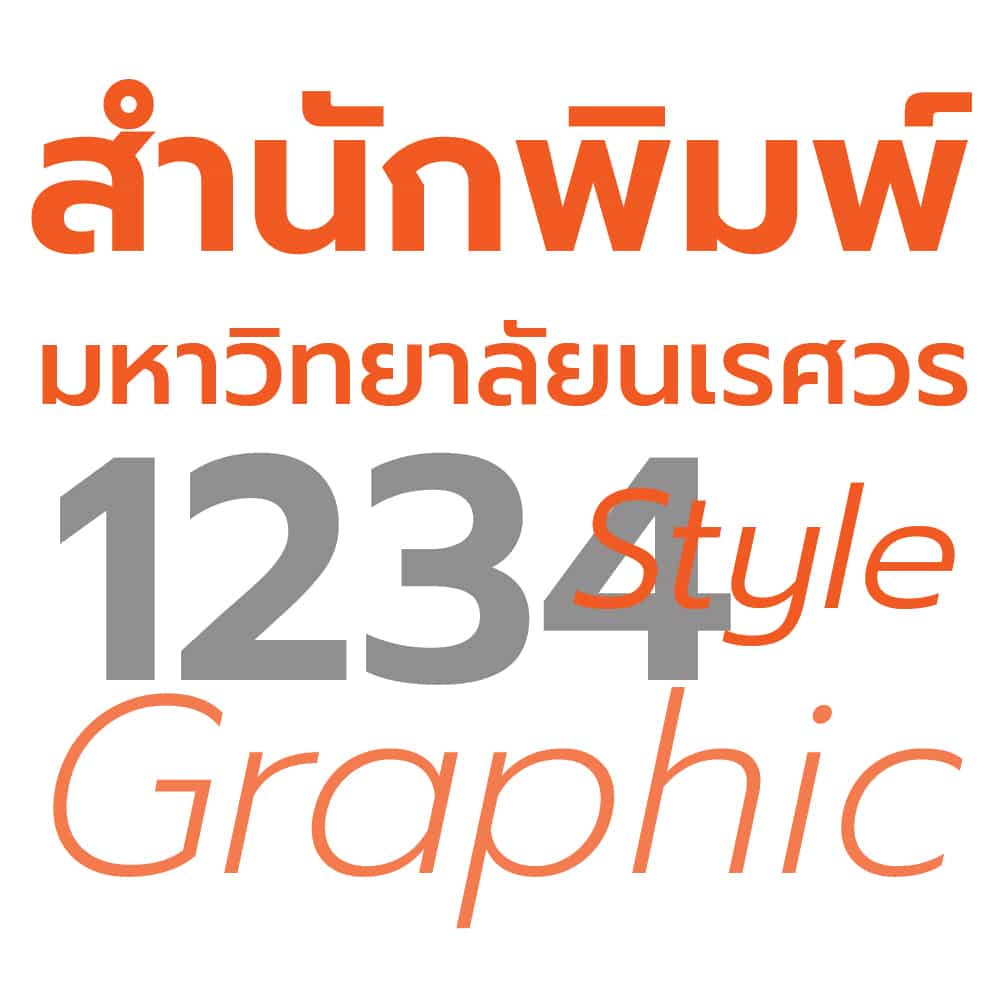
เป็น ฟอนต์ ไทย ที่ทาง Google ที่ออกแบบโดย Cadson Demak เป็นฟอนต์ลักษณะที่ไม่มีหัว เหมาะสำหรับการทำหัวเรื่อง หัวข้อ สื่องานโฆษณาต่าง ๆ ใครสนใจสามารถไปโหลดกันได้เลยที่นี่ Link
2. Kanit
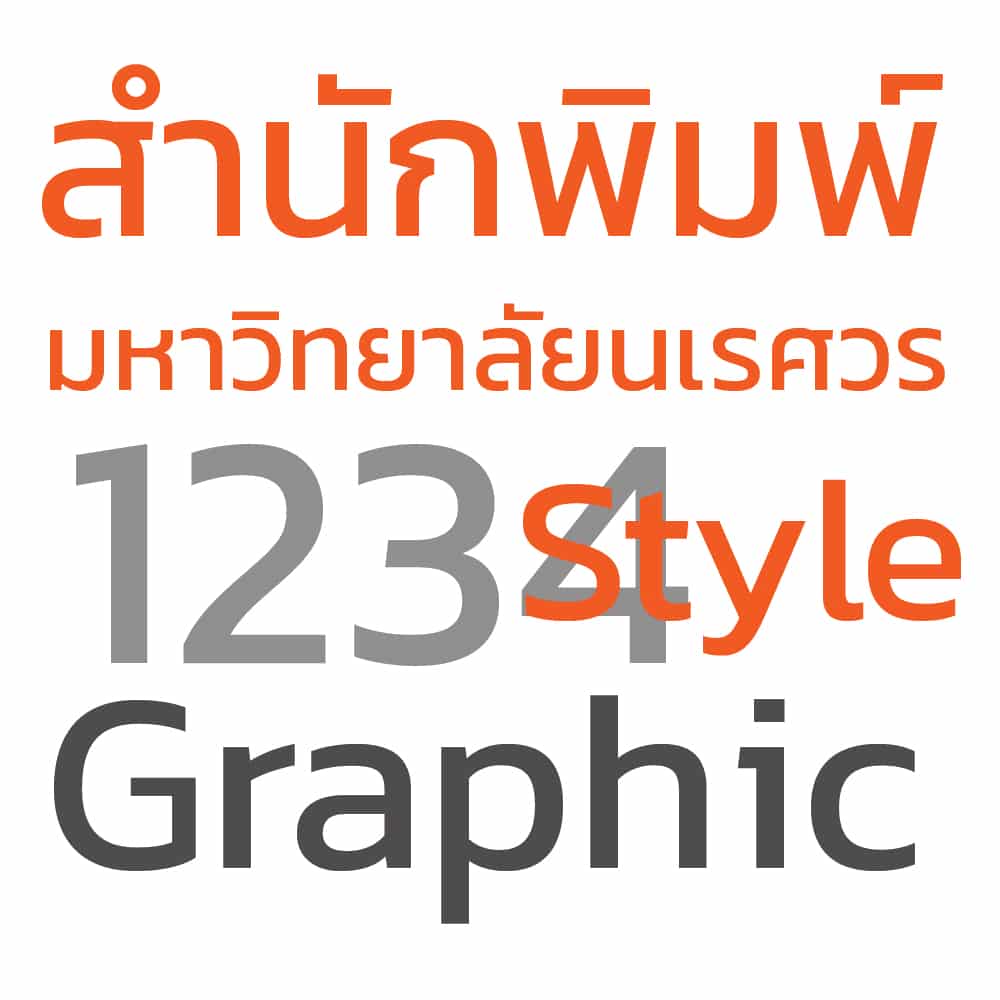
เป็นอีก 1 ฟอนต์ไทยที่ได้รับความนิยมอย่างมากจากทาง Google ที่ออกแบบโดย Cadson Demak เป็นฟอนต์ลักษณะที่ไม่มีหัวคล้าย ๆ กับฟอนต์ Promt เหมาะสำหรับ การทำปกหนังสือ ปกรายงาน หัวเรื่อง หัวข้อ สื่องานโฆษณาต่าง ๆ ใครสนใจสามารถไปโหลดกันได้เลยที่นี่ Link
3. Mitr
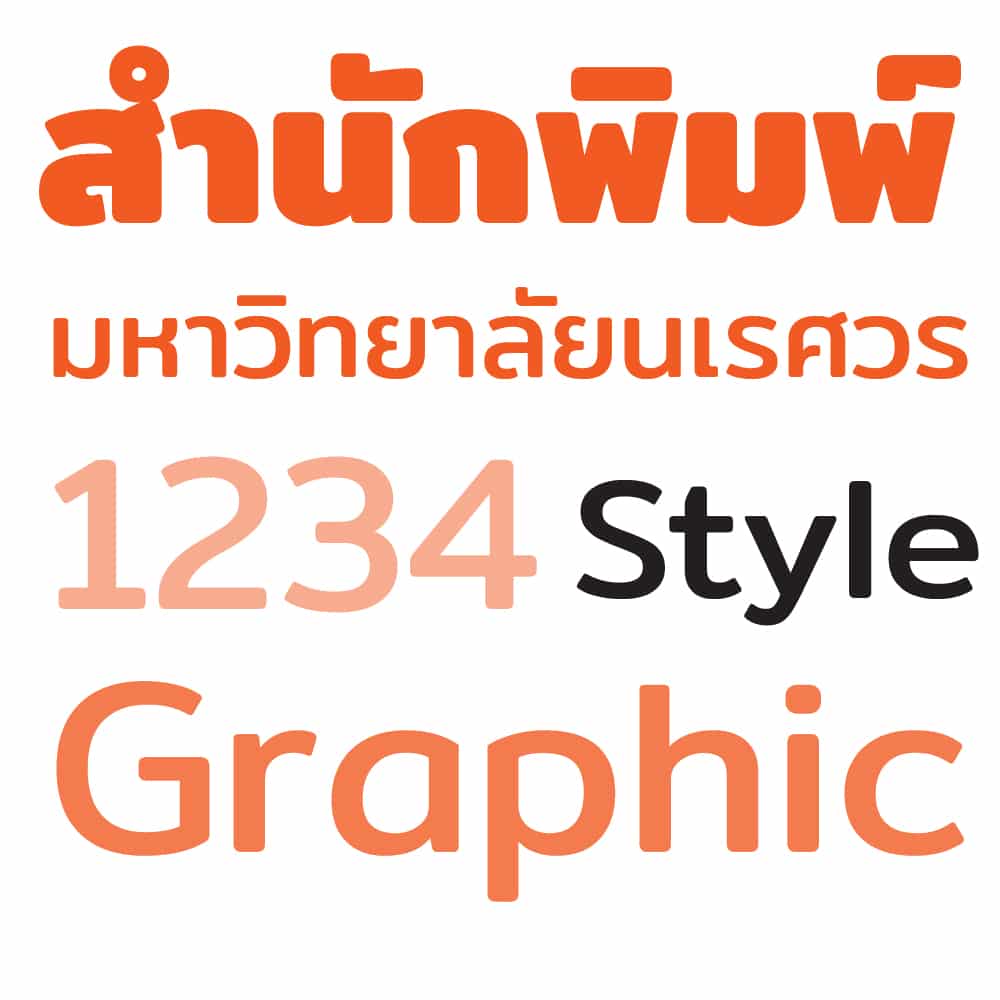
อีกฟอนต์ที่ได้รับความนิยมอย่างมากจากทาง Google เช่นเดิมที่ออกแบบโดย Cadson Demak เป็นฟอนต์ลักษณะที่ไม่มีหัวคล้าย ๆ แต่มีความละมุนออนโยน มีส่วนโค้งมากกว่าฟอนต์ Kanit หรือ Promt เหมาะสำหรับ การทำปกหนังสือ ปกรายงาน หัวเรื่อง หัวข้อ สื่องานโฆษณาต่าง ๆ ที่ดูไม่แข็งจนเกินไปทำให้งานออกแบบของเราดูสมูทมากยิ่งขึ้น ใครสนใจสามารถไปโหลดกันได้เลยที่นี่ Link
4. FC-lamoon
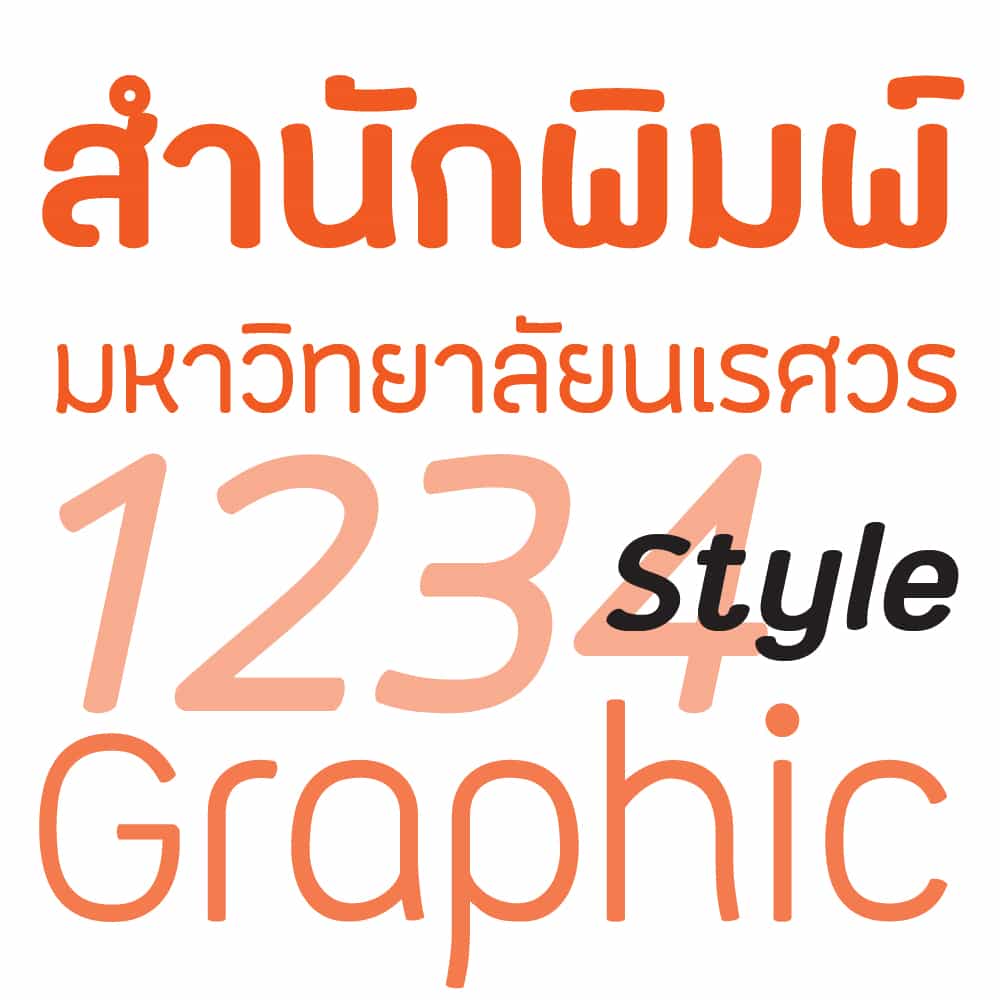
ฟอนต์ไทยที่ออกแบบมาด้วยความนุ่มนวล ลักษณะฟอนต์ที่ไม่มีหัว ให้ความรู้สึกที่สบาย ๆ เหมาะสำหรับ การทำปกหนังสือ ปกรายงาน หัวเรื่อง หัวข้อ สื่องานโฆษณาต่าง ๆ ที่ไม่ต้องการความตึงเครียดทำให้สื่อสารกับผู้พบเห็นได้สบาย ๆ มากยิ่งขึ้น สนใจสามารถไปโหลดกันได้เลยที่นี่ Link
5. Cloud
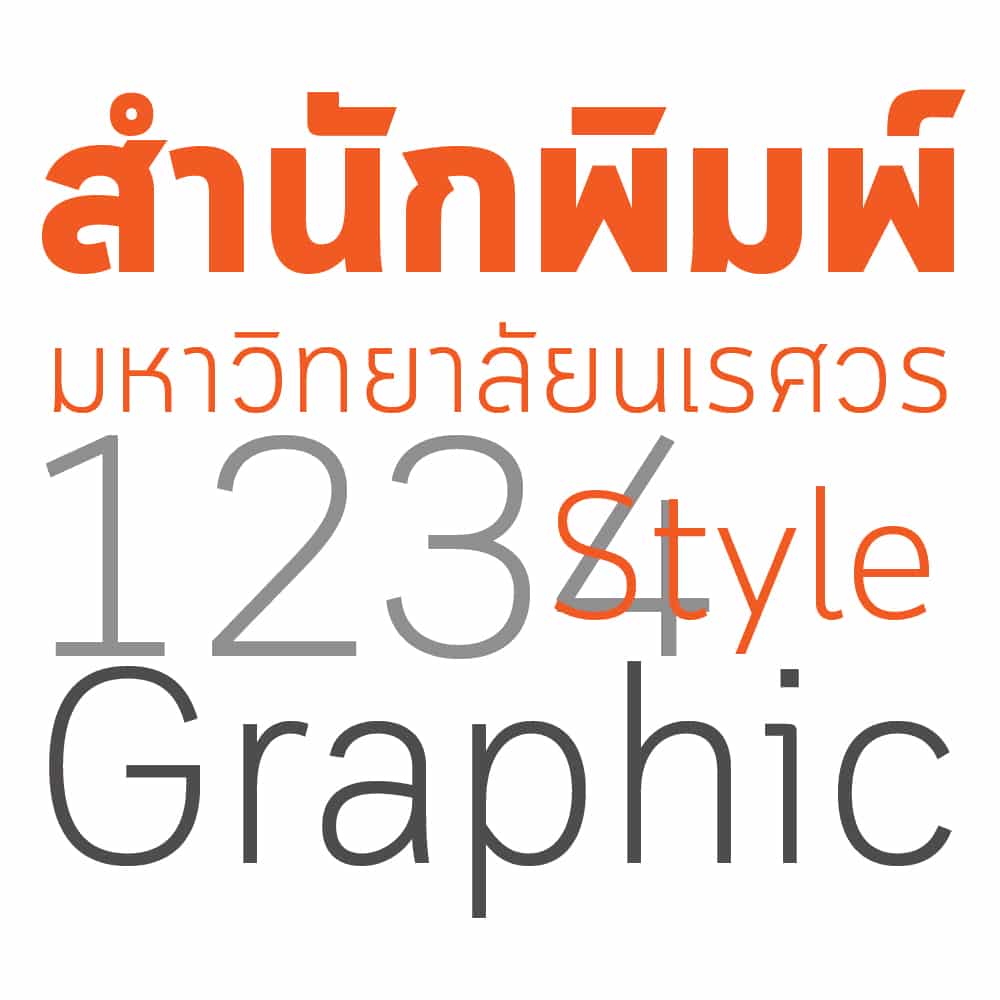
เป็นอีกฟอนต์ที่ทีมงานออกแบบชอบใช้ เหมาะสำหรับ การทำปกหนังสือ ปกรายงาน หัวเรื่อง หัวข้อ สื่องานโฆษณาต่าง ๆ ทำให้งานขอเราดูเป็นทางการและมีความน่าเชื่อถือมากยิ่งขึ้น ให้อารมณ์ที่แข็งแกร่ง ใครสนใจสามารถไปโหลดกันได้เลยที่นี่ Link
6. Supermarket
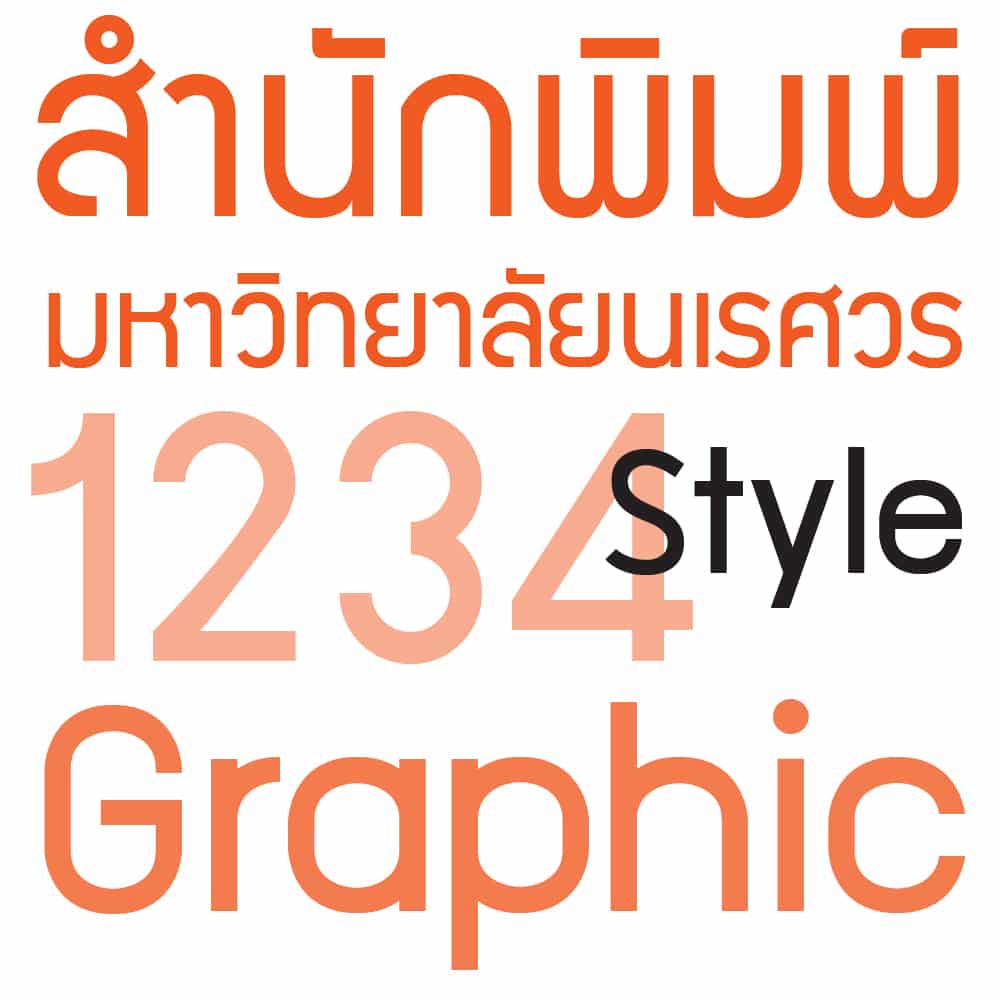
ฟอนต์ในตำนานที่เมื่อนักออกแบบพูดถึงฟอนต์ที่เป็นลักษณะไม่มีหัวและใช้งานใบการออกแบบแรก ก็คงต้องตอบเป็นเสียงเดียวกันว่า Supermarket ซึ่งปัจจุบันก็ยังเป็นดาวค้างฟ้าที่ยังคงได้รับความนิยมเป็นอย่างมาก เหมาะสำหรับ การทำปกหนังสือ ปกรายงาน หัวเรื่อง หัวข้อ สื่องานโฆษณาต่าง ๆ ทำให้งานขอเราดูเป็นทางการและมีความน่าเชื่อถือ ใครสนใจสามารถไปโหลดกันได้เลยที่นี่ Link
7. Sukhumvit Set
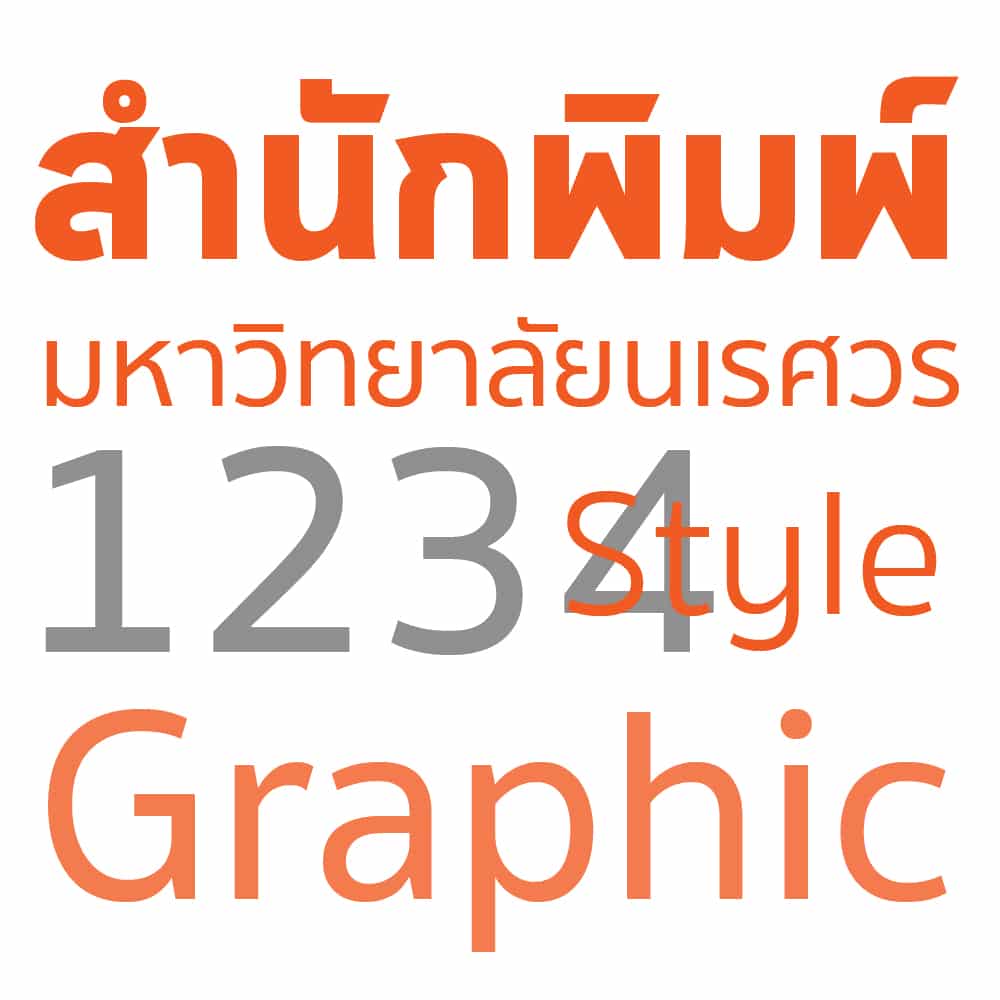
เป็นฟอนต์ที่มาพร้อบกับระบบปฏิบัติการของ Mac ที่ผู้ใช้งาน Mac OS X สามารถใช้งานได้ฟรีเลย เพราะเป็นฟอนต์ที่มากับระบบปฏิบัติการ ลักษณะของฟอนต์ที่ไม่มีหัว เหมาะสำหรับ การทำปกหนังสือ ปกรายงาน หัวเรื่อง หัวข้อ สื่องานโฆษณาต่าง ๆ
8. เอกมัย มาตรฐาน (Ekkamai Standard)
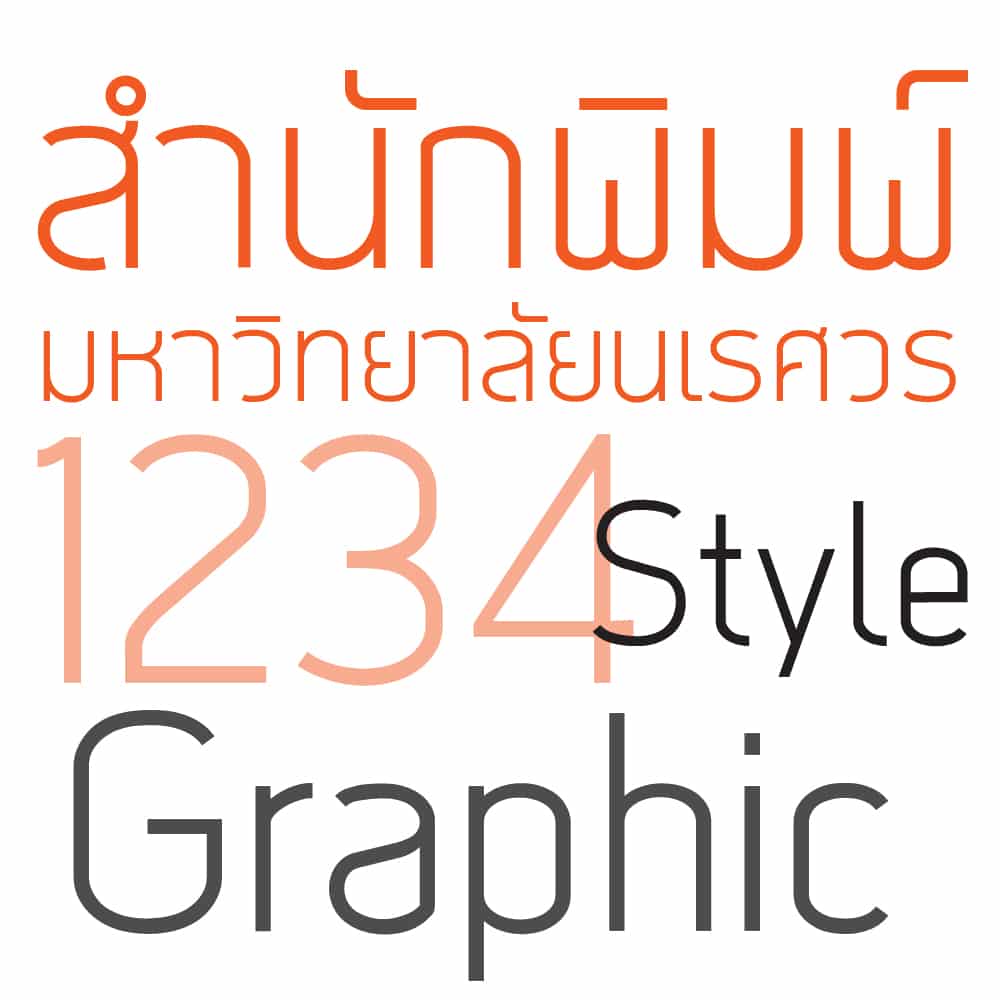
เป็นฟอนต์ที่มีเอกลักษณ์ ในเรื่องของความบางทำให้นำไปใช้ในงานออกแบบแล้วให้ความรู้สึกที่เรียบง่ายสะอาดตา เหมาะสำหรับ การทำปกหนังสือ ปกรายงาน หัวเรื่อง หัวข้อ สื่องานโฆษณาต่าง ๆ และต้องการสื่อสารกับผู้พบเห็นในลักษณะที่เรียบง่าย สบาย ๆ สนใจสามารถไปโหลดกันได้เลยที่นี่ Link